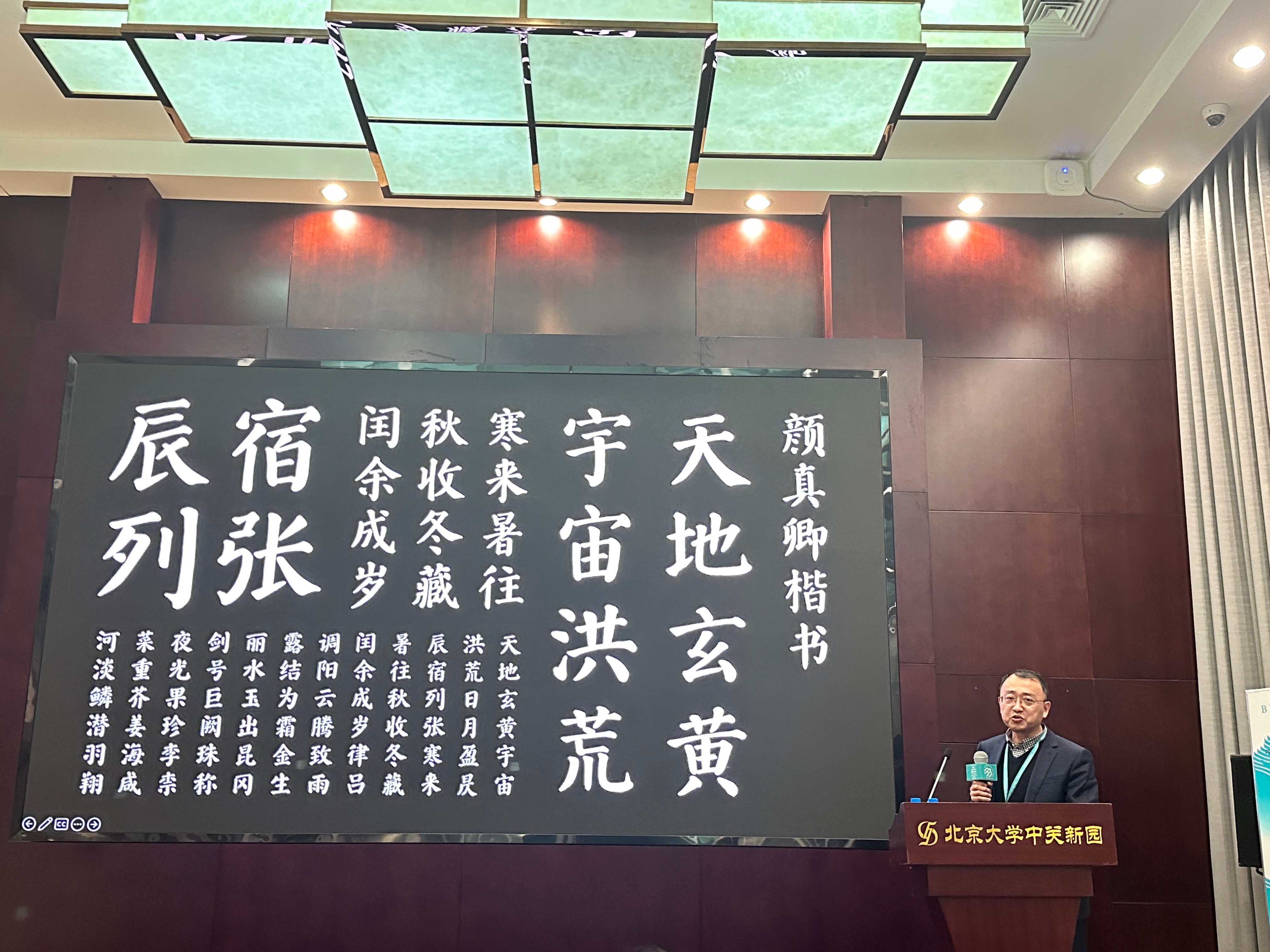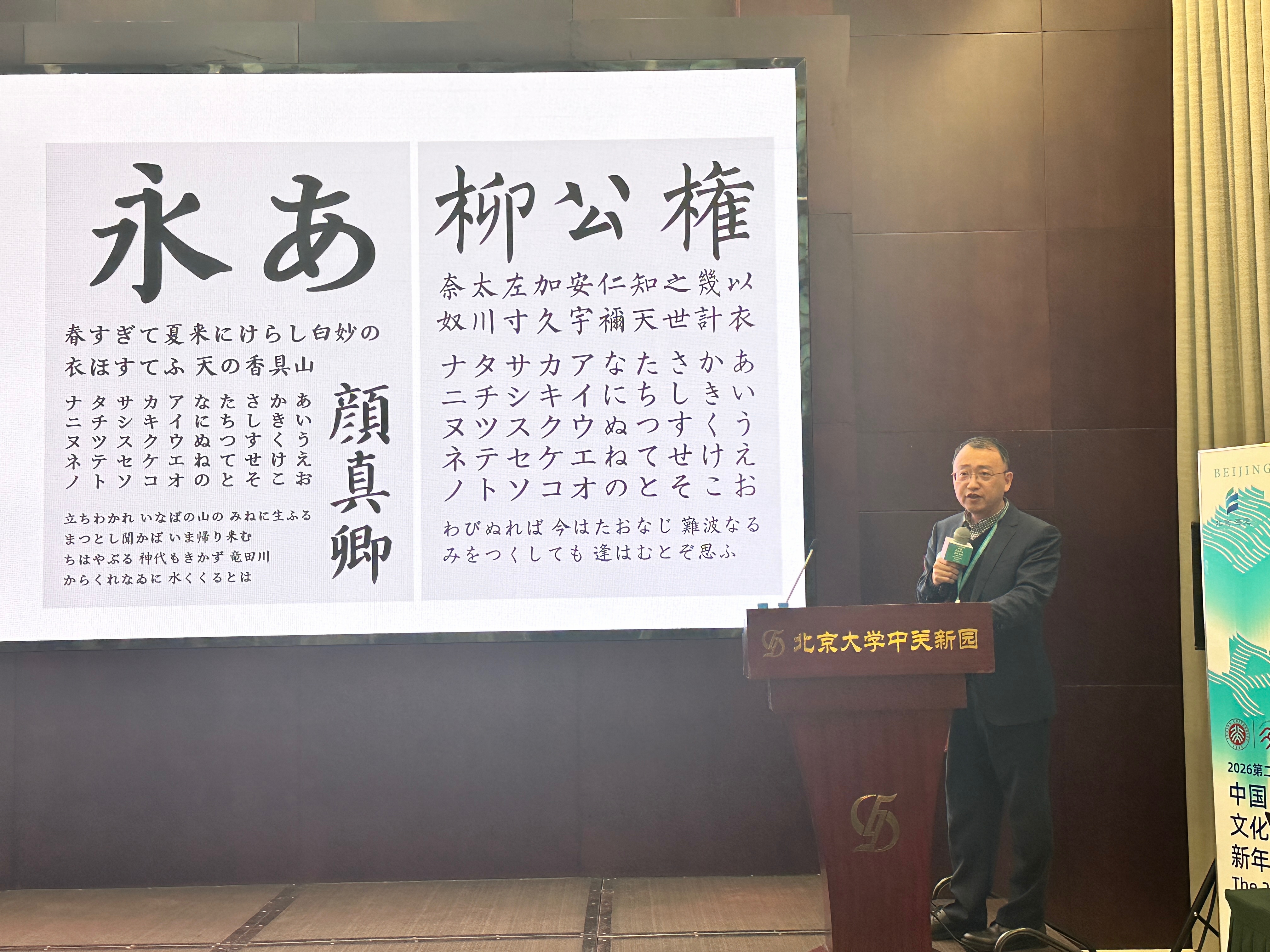
方正电子张建国以《AI赋能中华精品字库工程,助力中华优秀文化传承发展》为题,系统介绍了方正电子以人工智能技术助力文化传承的创新实践。他重点分享了如何利用自主研发的AI辅助字体设计技术,对仅存二百余字的《洛神赋》千年法帖进行全卷还原,该成果于《中国书法大会》第二季中亮相,实现了文化遗产的数字化“重生”。此项技术应用于“中华精品字库工程”,成功推动包括颜真卿、柳公权、赵孟頫等名家字体的数字化开发。目前,工程已发布47款书法字体,并通过国家语言资源服务平台开放下载,让历代书法艺术融入当代生活。
与此同时,方正字库持续推动中华字体文化走向世界,于2024年11月在东京发布颜真卿楷书、柳公权楷书、苏轼行书、爨宝子碑楷书、等四款日文版字体,开启汉字文化的国际对话。
张建国表示,在AI时代,科技与文化的深度融合已成为推动文明传承与创新的关键动力。面向未来,方正电子将继续依托人工智能技术,在文化遗产数字化活化等领域深化探索,积极参与构建开放协同的产业生态,助力实施国家文化数字化战略,为推动中华优秀传统文化创造性转化、创新性发展,贡献“技术+文化”的融合实践。